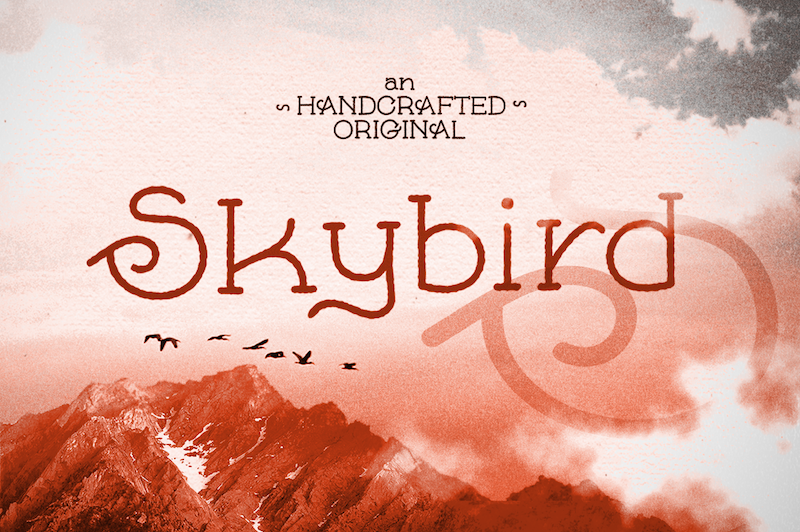
Skybird Font
A Skybird Font é uma nova serif moderna que se destaca entre as demais por sua originalidade e criatividade. Inspirada no estilo retro, ela também oferece uma versão limpa e minimalista perfeita para design atual. Ideal tanto para projetos vintage quanto para ambientes de tipografia contemporâneos, a Skybird pode ser adquirida com todas as suas licenças básicas em apenas $9,99 através do site da Hamilton. Esta fonte é uma excelente escolha para designers que buscam dar um toque único e memorável aos seus projetos digitais, seja por meio de texto embutido ou impressão. Se você está procurando uma opção sofisticada com personalidade, a Skybird pode ser o complemento perfeito para seu design.